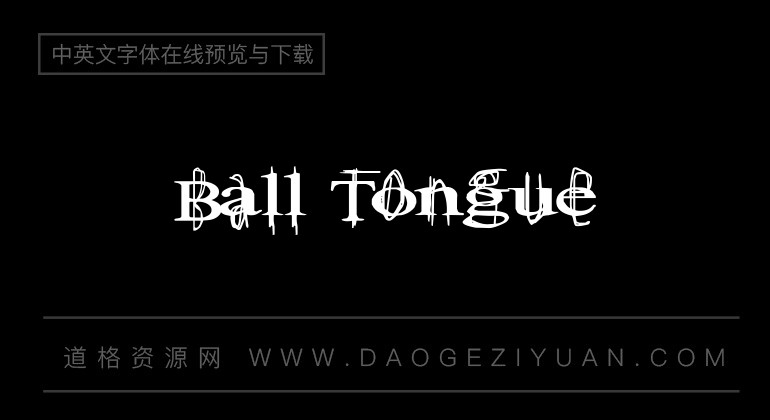
Ball Tongue
Ball Tongue 是一种英文字体,由英国设计师 Jonathan Barnbrook 创作,于1996年发行。它是一种表现力强、视觉上有趣的字体,拥有浓厚的街头风格,可以很好地表达出流行文化的特色。Ball Tongue 的特点是字体设计上有趣、突出,字体的笔画比较粗糙,有着较强的表现力,可以让文字充满活力。它适用于流行文化的设计,可以在海报、T恤、音乐封面等场合使用,也可以用于品牌标识的设计。
Ball Tongue是一款非常不错的手写艺术字体,具有很好的视觉感,适合于文化类的宣传设计、商业类品牌的广告和产品包装设计以及个性化文字排版等较多场景。